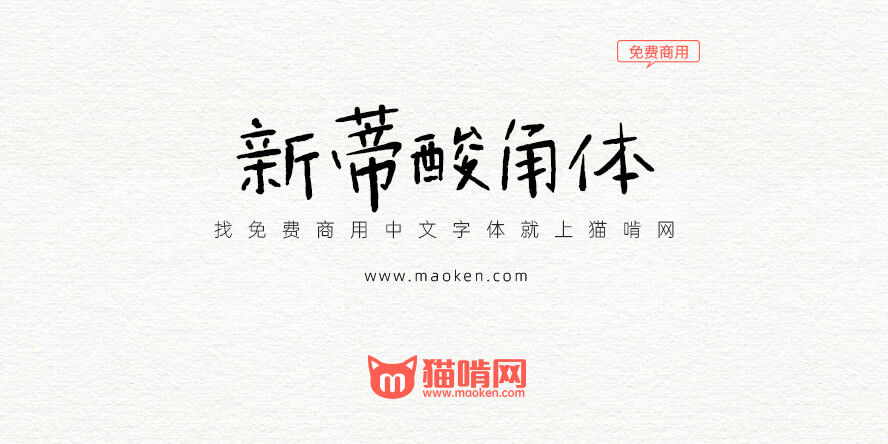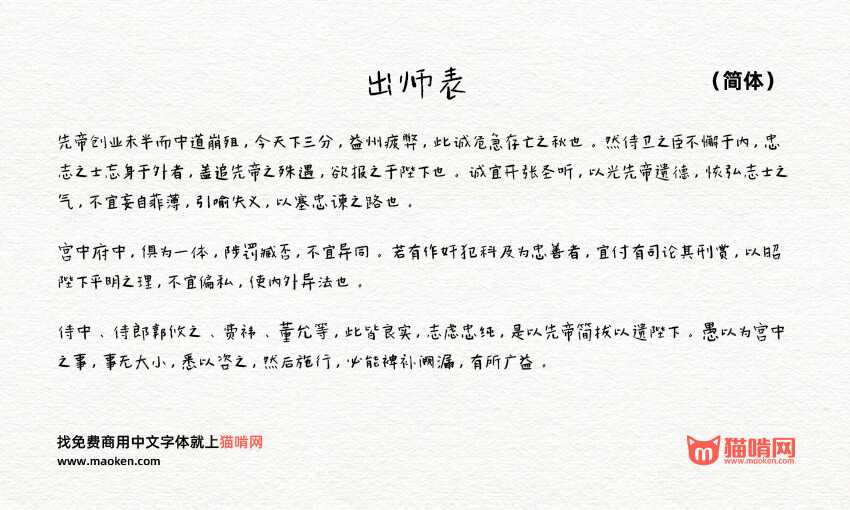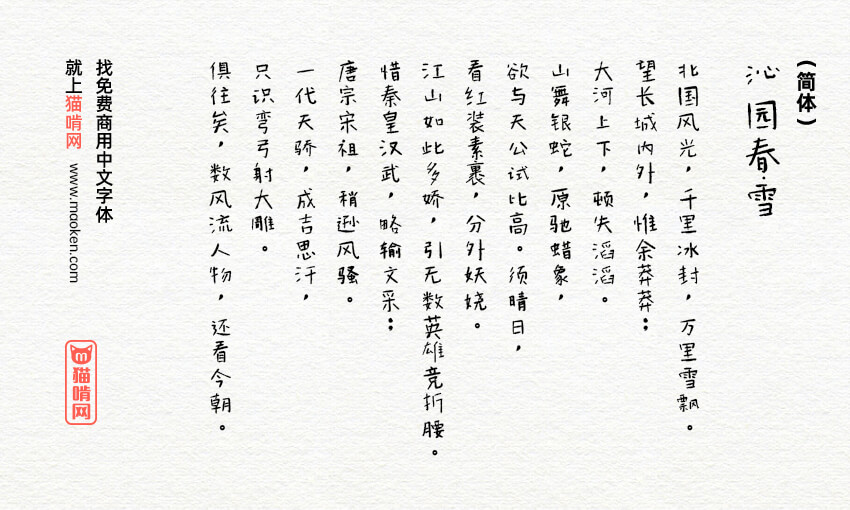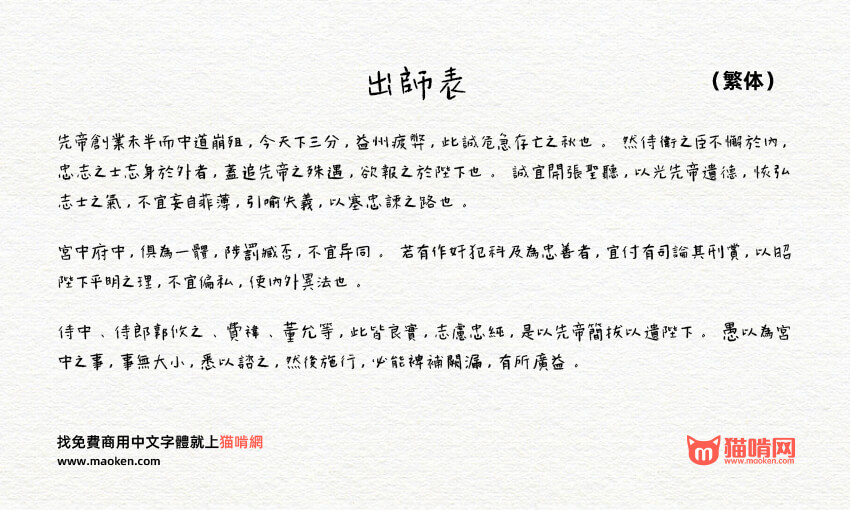
PS字体名:新蒂酸角体 | 字体版本:Version 1.00(2021/09/01) 更新记录 |
字体作者:新蒂字体(中国大陆) | 字体字重:1个 |
新蒂酸角体是新蒂字体在2022年推出的一款针对个人和小型企业的免费商用字体。新蒂酸角体正如它的名字一般,形态各异的外壳中,蕴藏着美味的果肉。这款非等宽字体,也使文本在跃动的行间,流露出醒目舒适的书写。新蒂酸角体支持超过10000+简体字、繁体字、拉丁字母,可以说是比较齐全了。